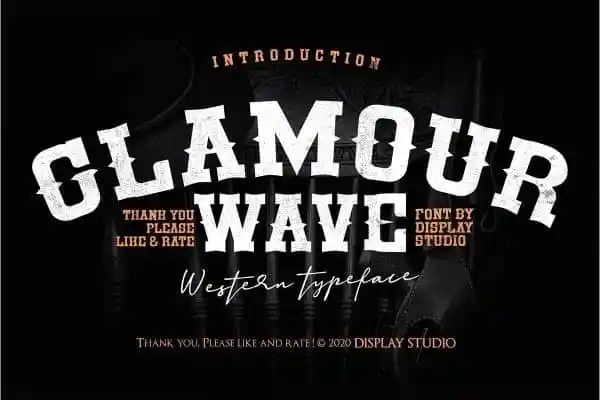
Glamour Wave Display Font – Download Grátis
Introduzimos a Glamour Wave Display Font, uma tipografia forte para uso de destaque com letras maiúsculas multilíngues, duas opções de letras alternativas e números e pontuação. Este tipo vem tanto em estilo regular quanto rústico. É perfeito para personal branding e publicidade. Esta tipografia é ideal para logotipos de marca, convites, cartas de cumprimentos ou qualquer projeto.